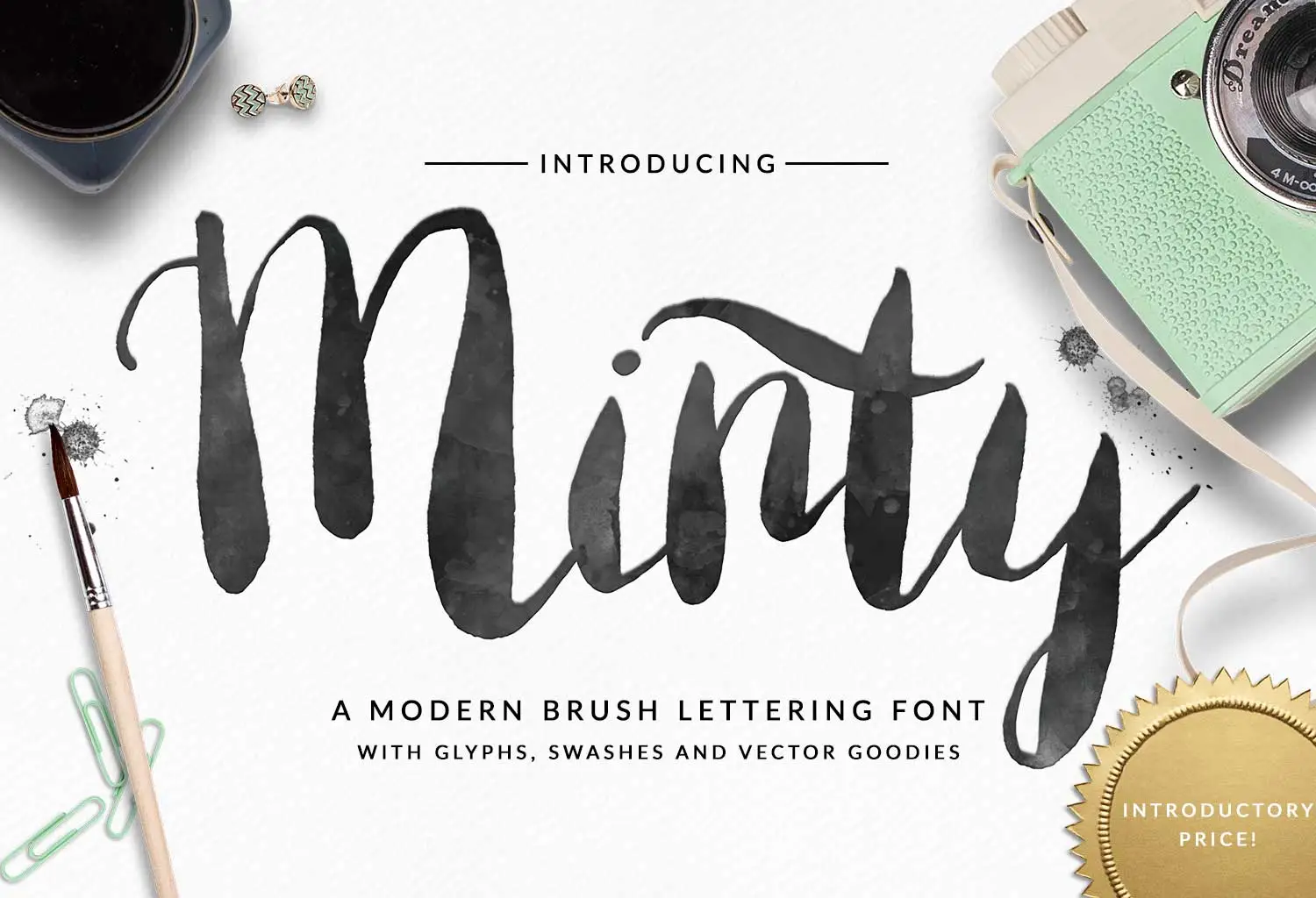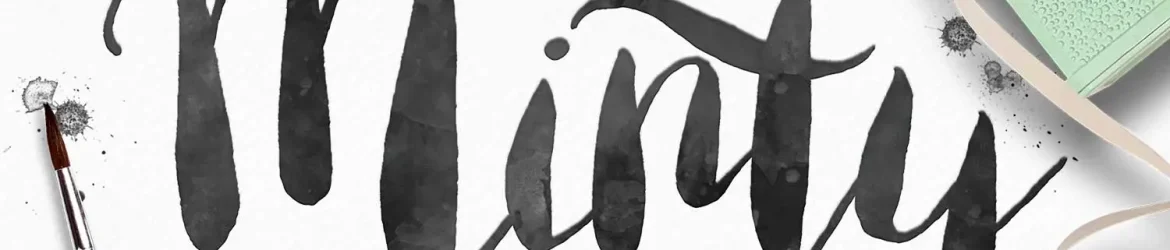
Minty Brush Font – Download Grátis
Olá! Estou aqui uma introdução a Minty, uma tipografia script feita com as mãos criativas, usando textura natural para criar um estilo brush pen. Minty Brush Font é perfeitamente adaptável ao design de postais de casamento ou você pode usar-a para criar designs únicos e inovadores dos seus logotipos, blogs, cartões de papelaria, marketing e revistas. Essa fonte sempre traz uma dose de excitação à sua criação. Sempre pronto para fazer a diferença em suas próximas projetos gráficos. Seja você um designer de postais de casamento ou criador de conteúdo digital, Minty Brush é a escolha certa para deixar seus designs mais atraentes e únicos.